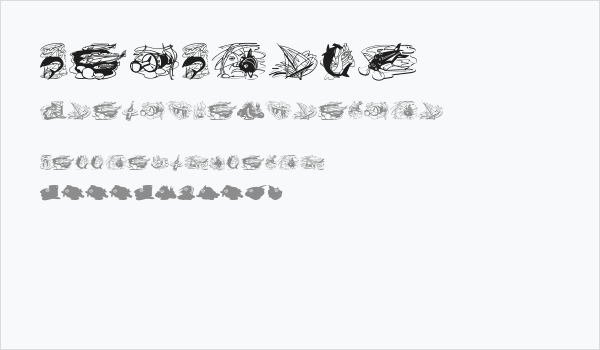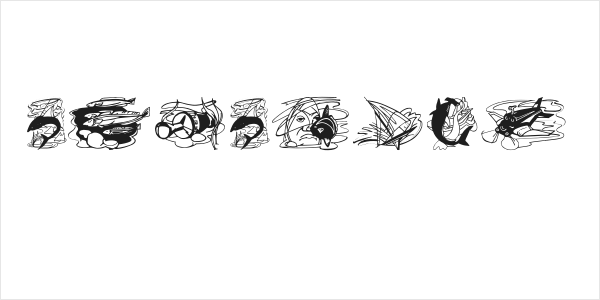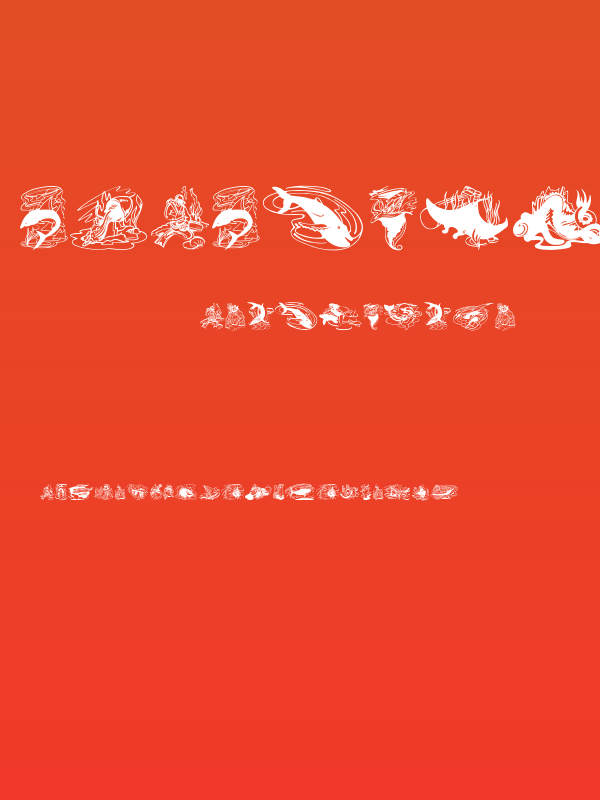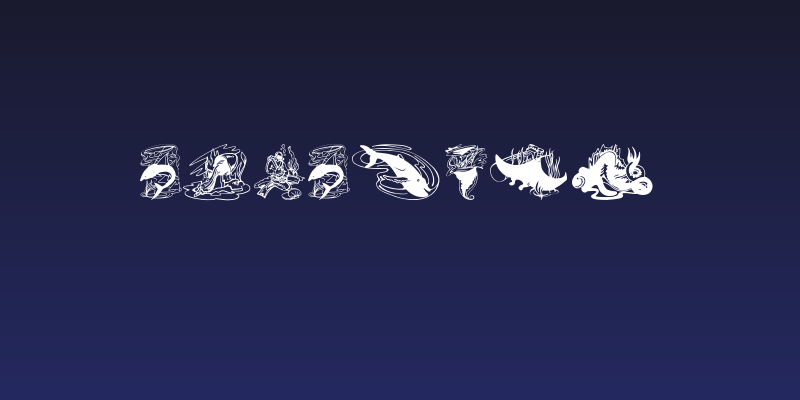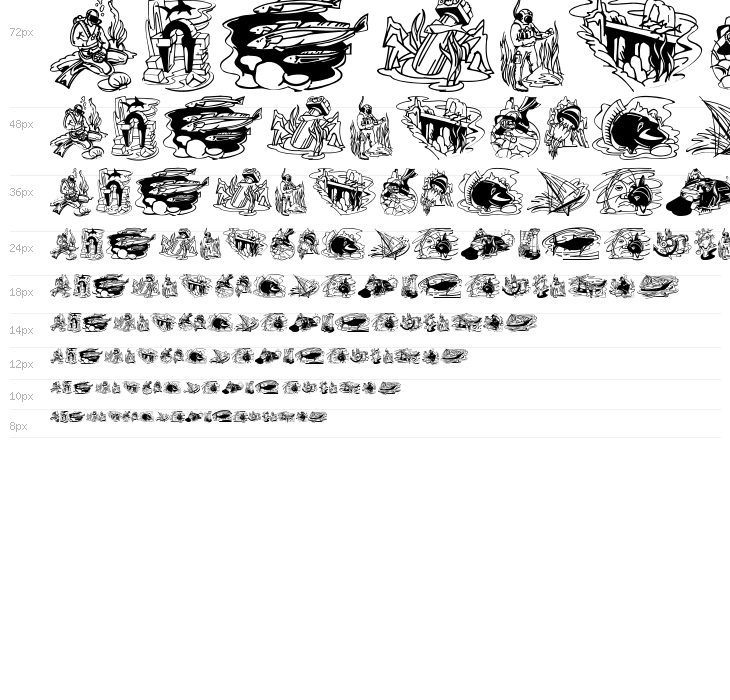
WetWorld Font
✎ Dingbats
| Cas d'utilisation | Logos, Decorative elements, Thematic artwork |
| Projets proposés | Ideal for ocean-themed posters, artistic projects, educational materials about marine life, or decorative elements in aquatic-themed events. |